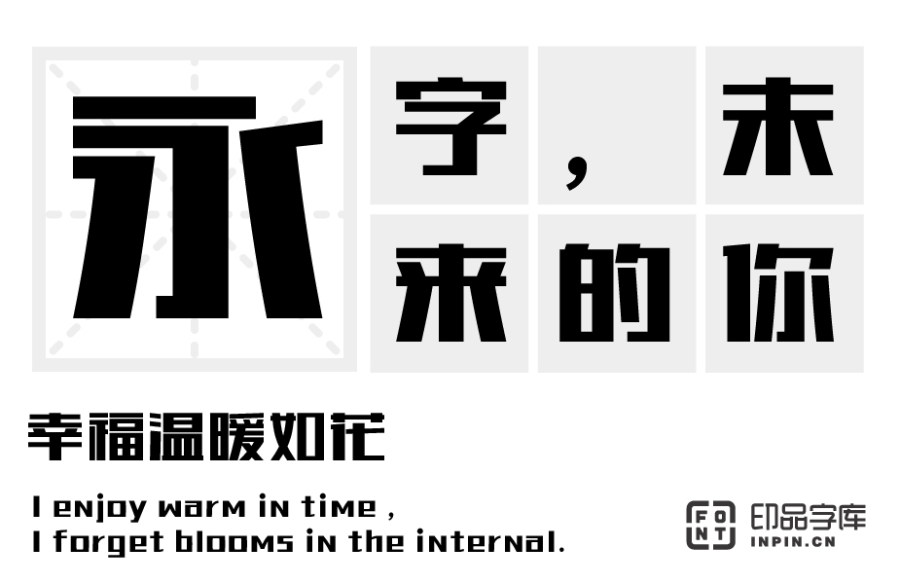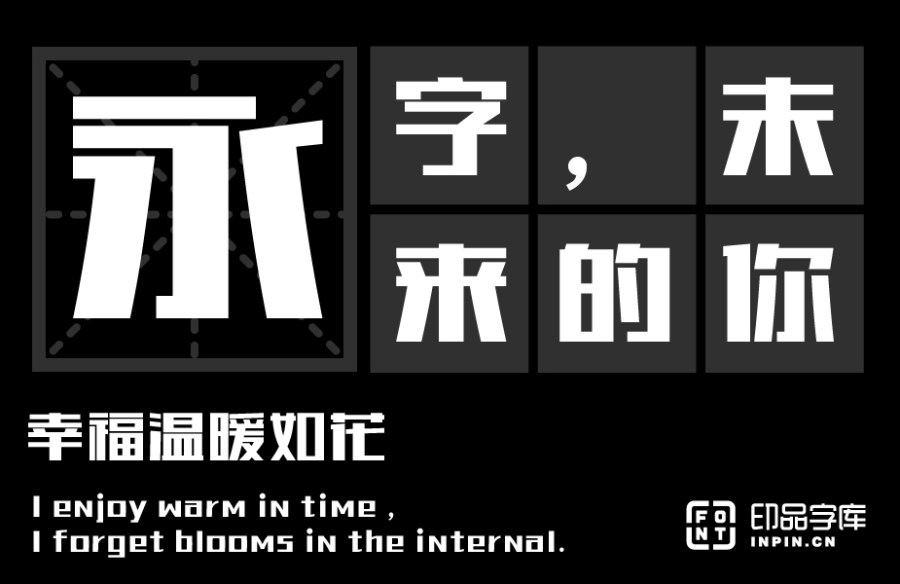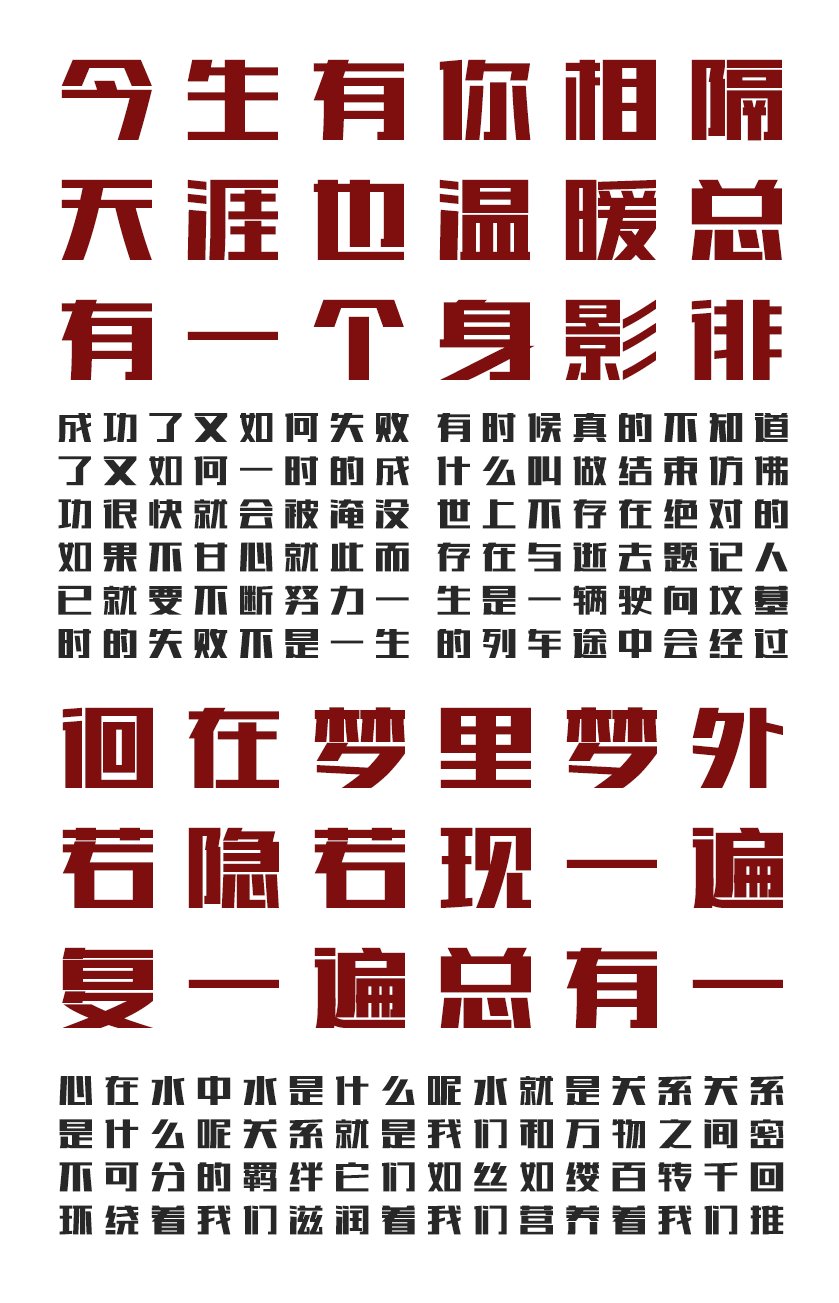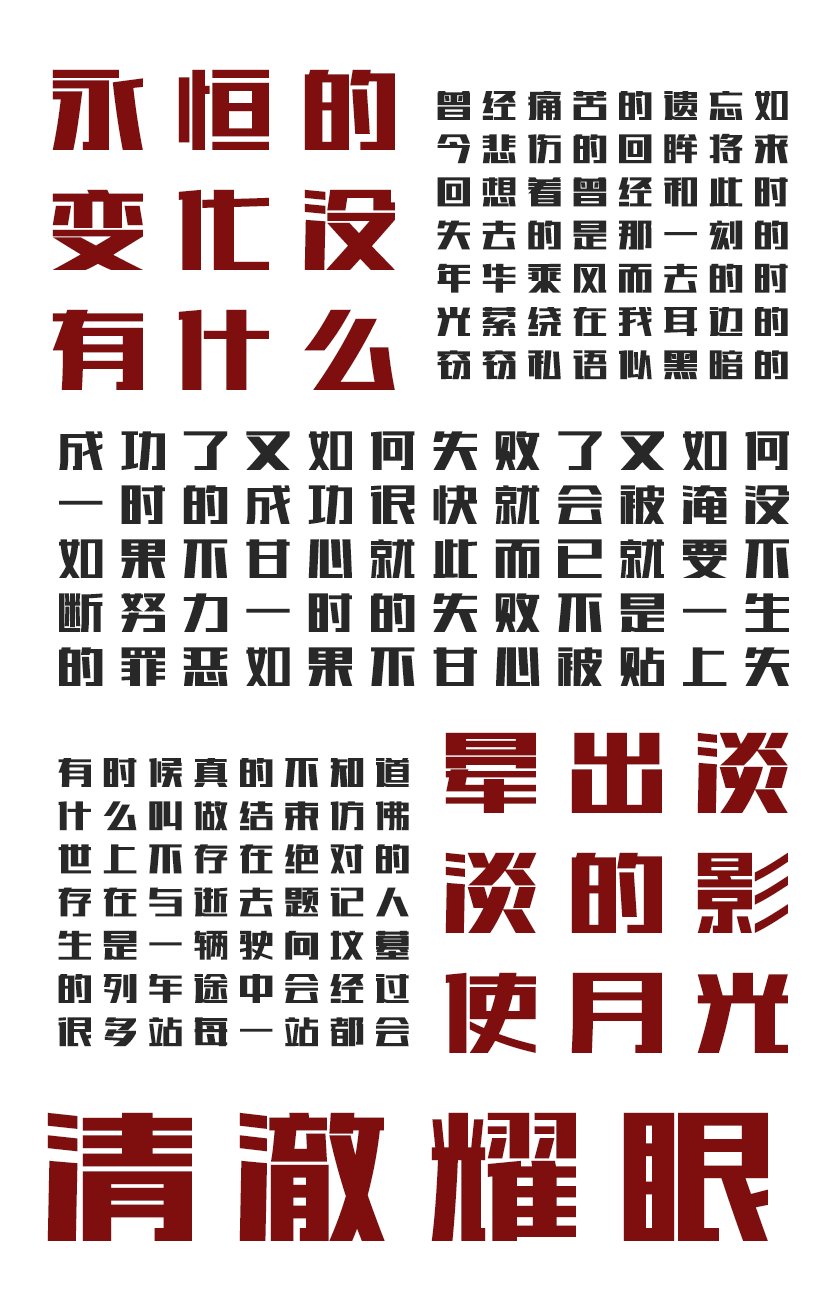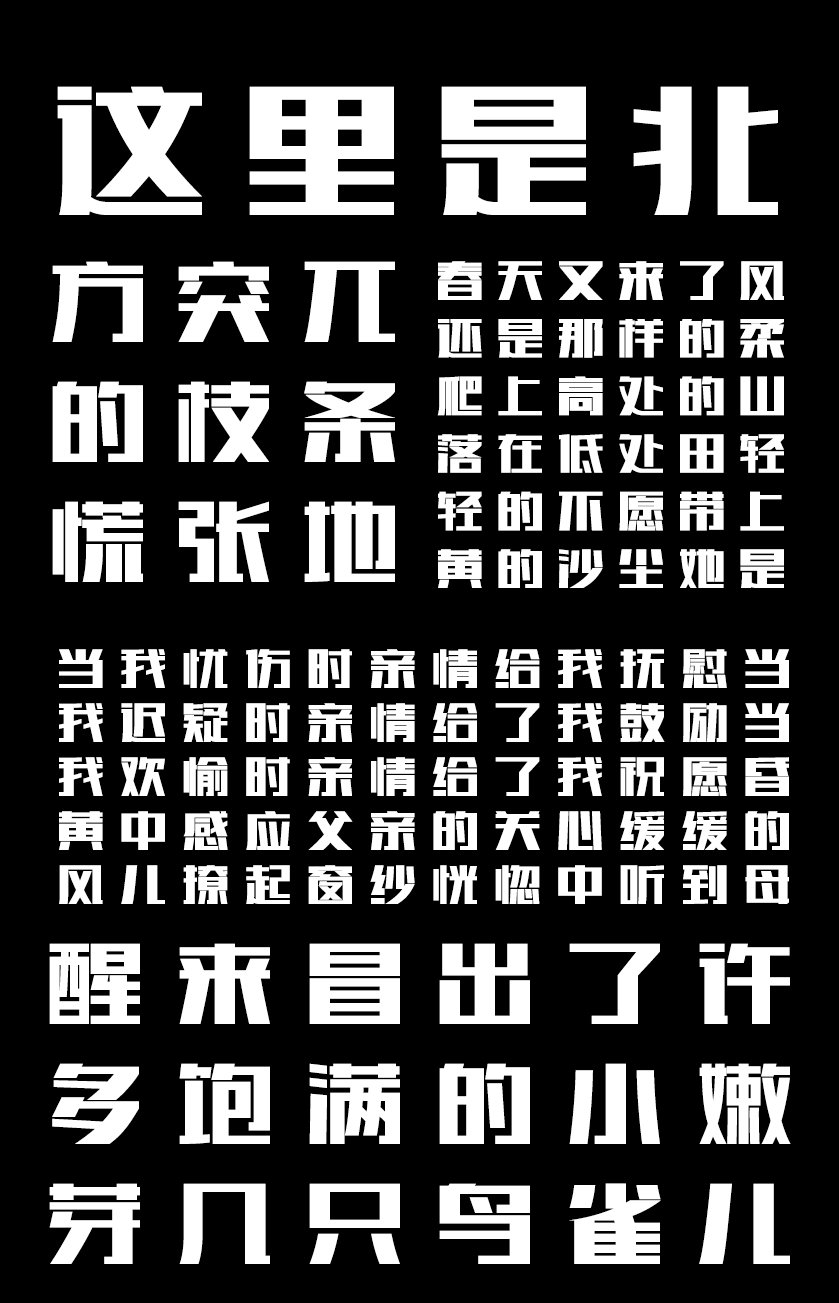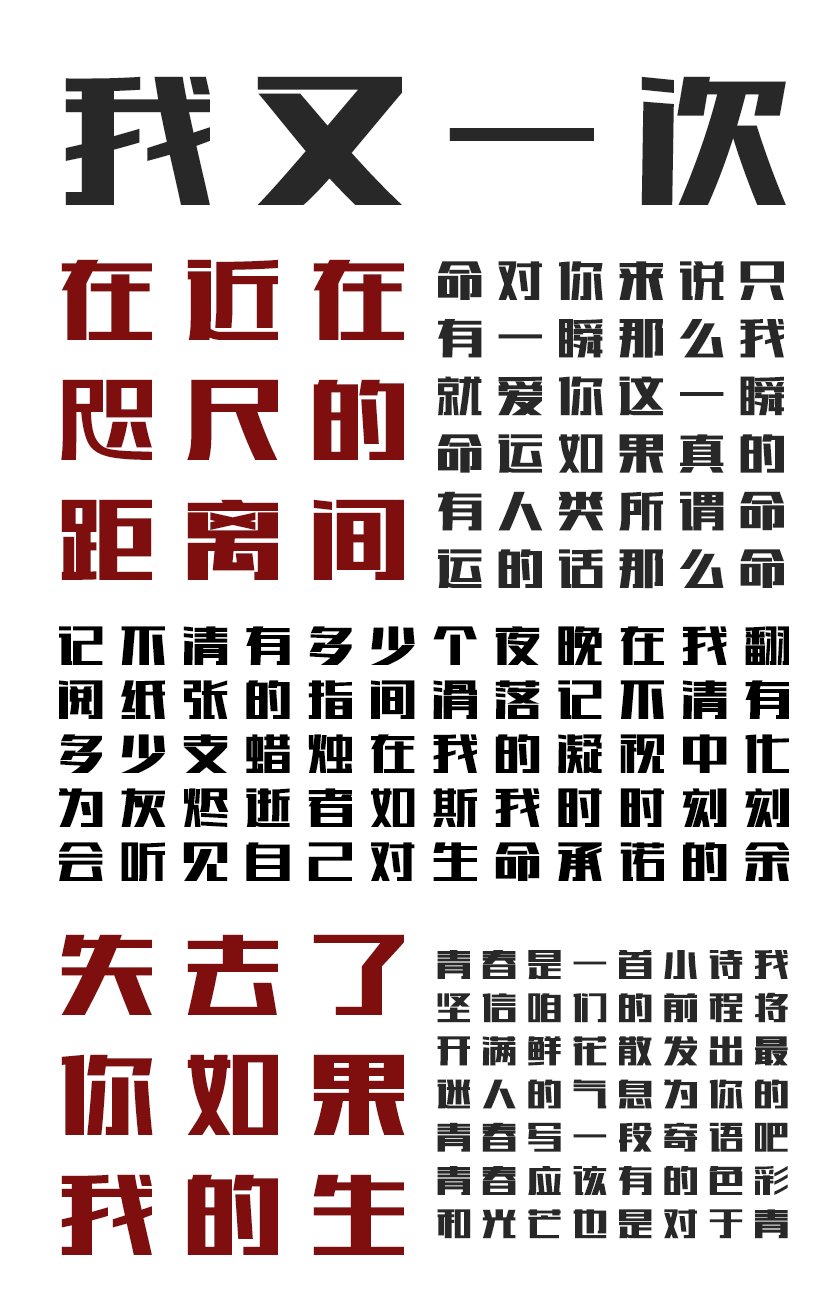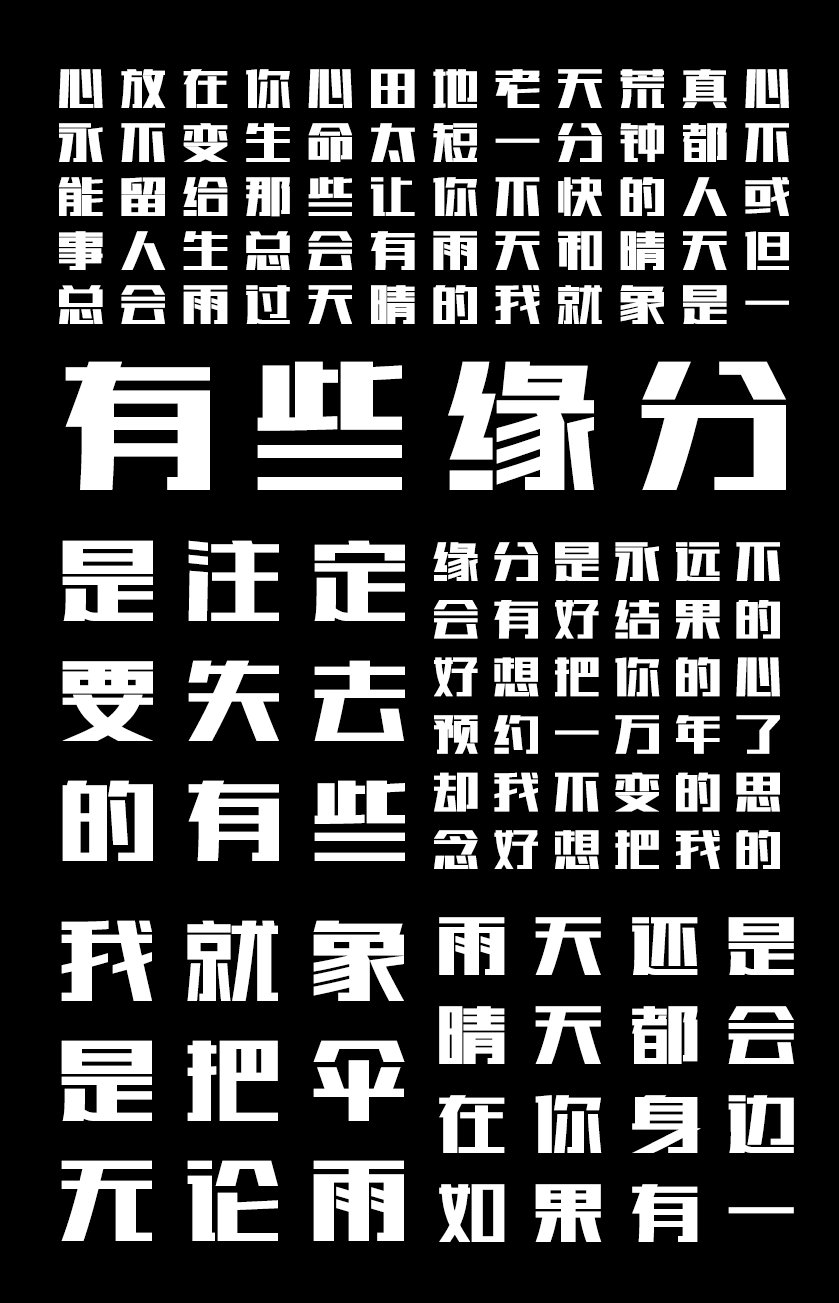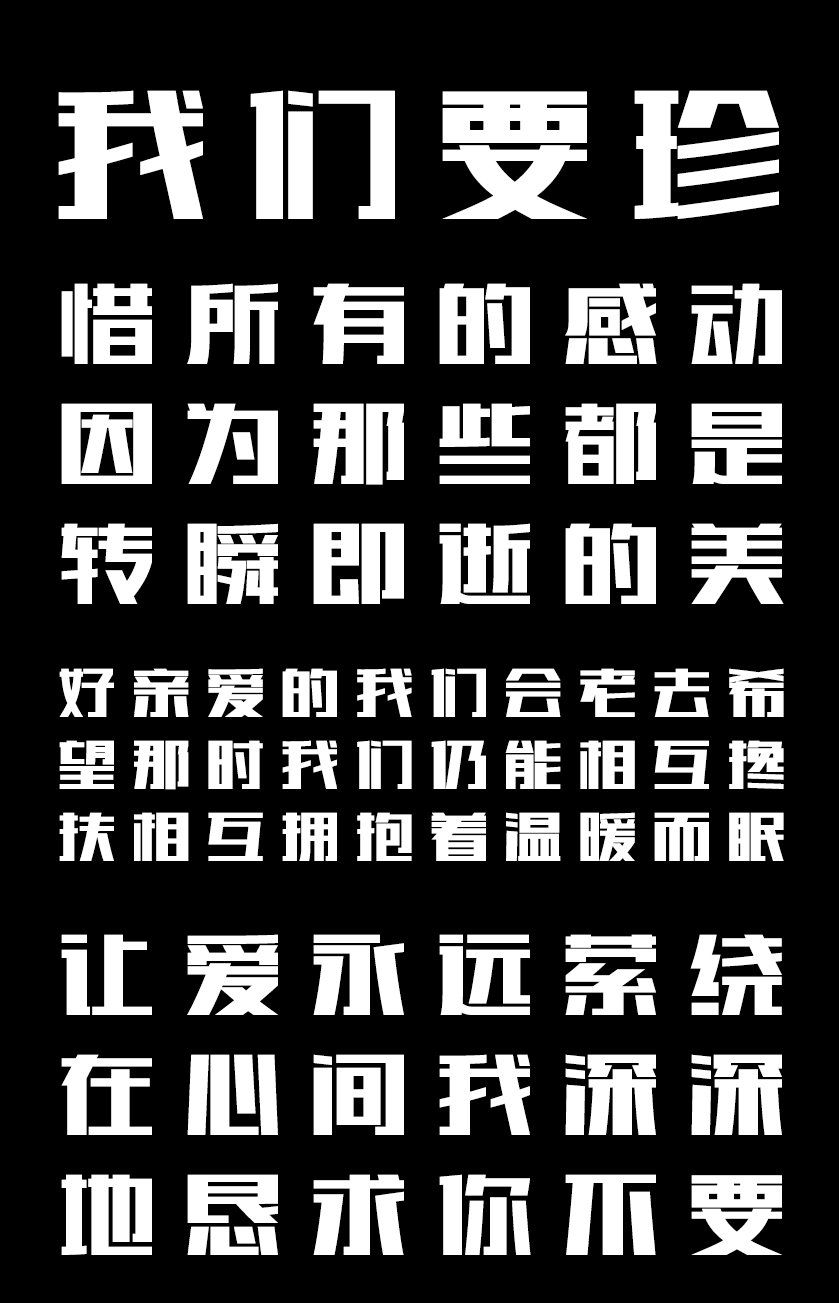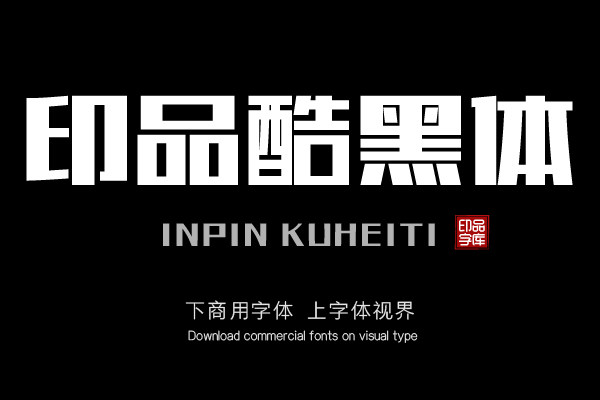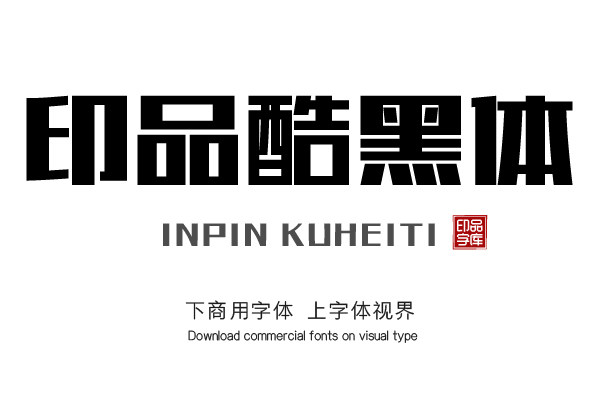
印品酷黑体是一款时尚简明且具艺术感的黑体字库,字体稳重充满力量,视觉冲击力较强。适用于电商、广告、标题类场景。单字授权
印品酷黑体整体形态粗犷,强有力度,撇、捺适度的采用曲线流畅的方式,使整个字形坚硬中又有优美的弧度,刚柔并济。整体结构基于黑体的横细竖粗的基本笔画特征,粗细分明,重心偏上,字面饱满,结构稳重大方,更加醒目,极具现代感。印品酷黑体是一款漂亮的标题字体,字形雄厚有劲,刚柔并济,时尚感极强,适用于电商、广告、标题等宣传场景。